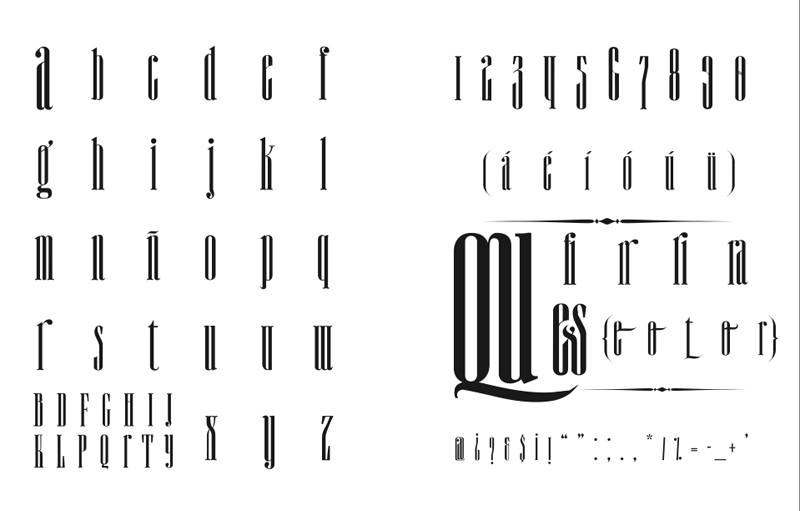
Font name: | Quinn |
Author: | MAGOfonts |
Note by MAGOfonts | |
Es una typo de display, no sirve para texto de corrido ni tiene ajustados los espaciados, aunque su uso va a criterio del diseƱador. Elegante y muy condensada, requiere que le den su espacio para que salga a ser vista :) |